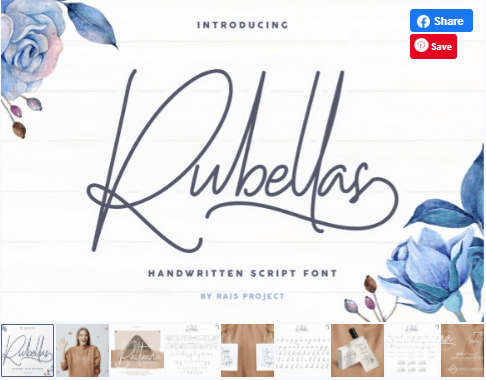
Rubellas Font
Rubellas - стильный и невероятно элегантный скриптовый шрифт. Он потрясающе смотрится на свадебных приглашениях, открытках с благодарностью, цитатах, поздравительных открытках, логотипах, визитных карточках и любом другом дизайне, требующем рукописного ввода.